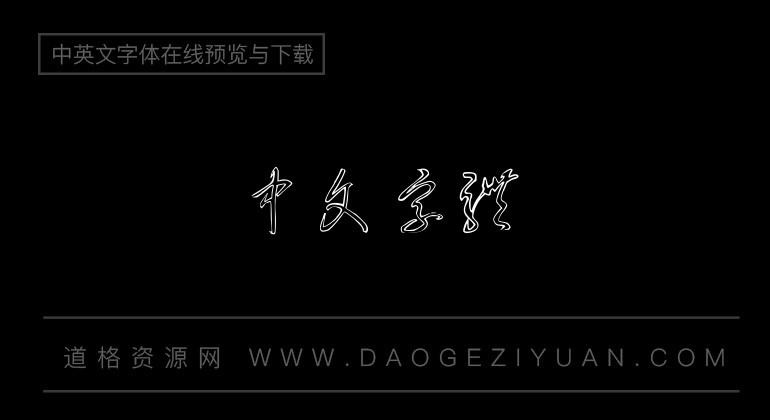
李洤迷宫草书
李洤迷宫草书是一款简繁混合字体,由李洤先生设计,以汉字传统笔画为基础,融合繁体字和简体字的特点,使其具有独特的字体风格。它具有清新的外观,更有利于阅读,在设计上更加精致,具有极好的可读性和视觉效果。
李洤迷宫草书是一款非常不错的手写艺术字体,具有很好的视觉感,适合于文化类的宣传设计、商业类品牌的广告和产品包装设计以及个性化文字排版等较多场景。